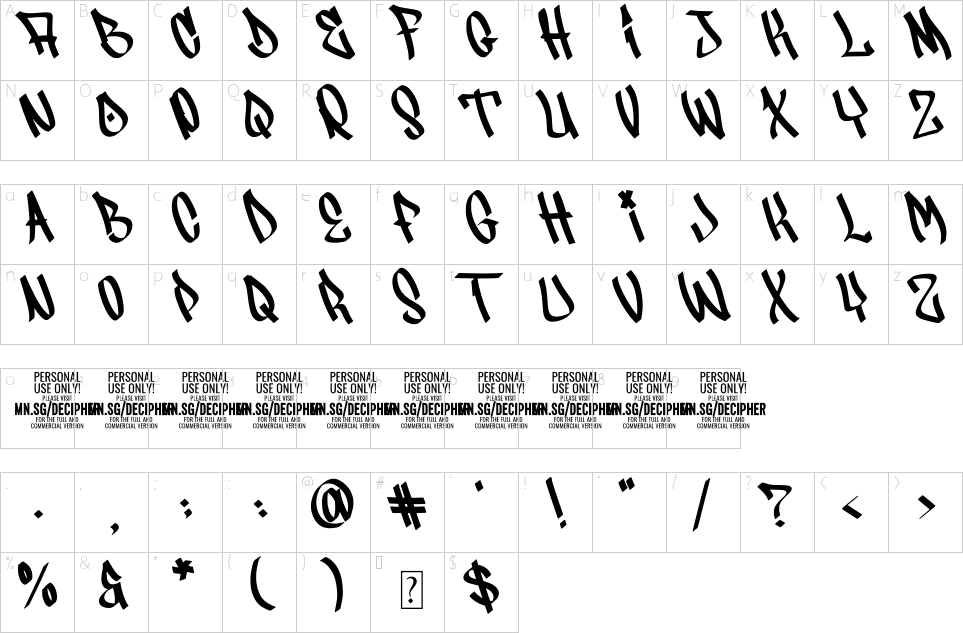
Decipher Font
A fonte Decipher foi criada por Måns Grebäck e oferece uma experiência de digitação precisa e elegante. Sujeitamente a várias aplicações, incluindo Windows e Mac, ela se destaca pela sua facilidade de uso e estética sofisticada. O design desta fonte é simplesmente envolvente, combinando elementos modernos com um toque mais clássico. Com Decipher na sua lista de fontes, você pode criar documentos tanto para uso pessoal quanto profissional, garantindo sempre um grau elevado de legibilidade e estilo elegante no design. Desfrute do conforto e da variedade que a Decipher traz à sua ferramenta de digitação. Esta fonte grátis é um excelente começo para qualquer criador de conteúdo ou designer.